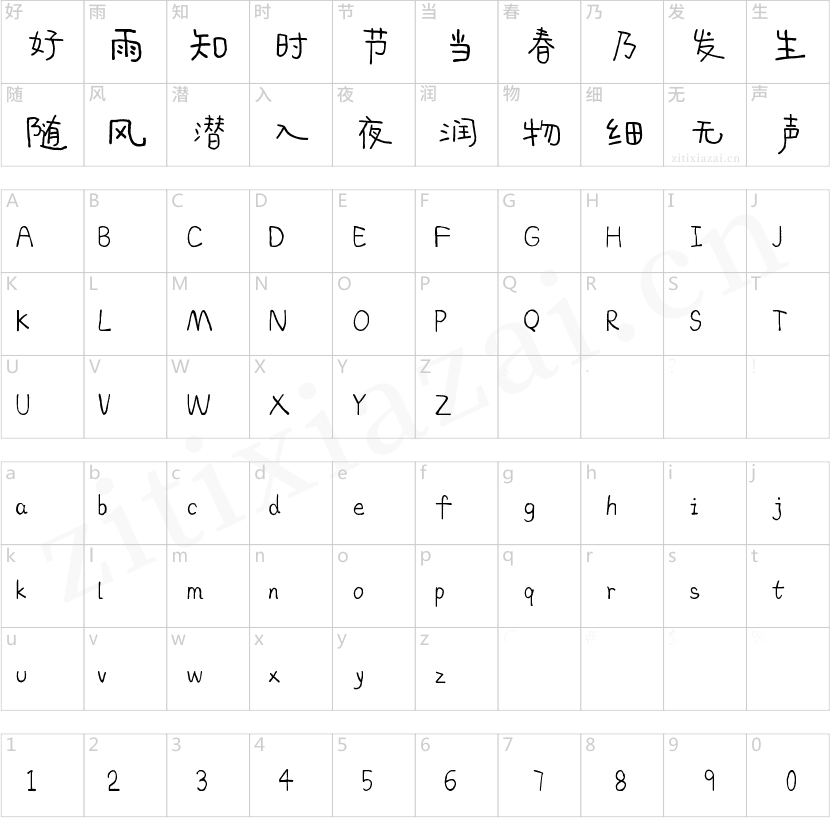
字魂90号-萌趣甜心体
字魂90号-萌趣甜心体,这款字体结构工整、笔画清晰,兼顾美观与易读性,适用于标题、正文、海报、包装、LOGO 等多种场景。字形优雅稳定,风格百搭耐看,适配日常排版与创意设计,让文字呈现更舒适、更具质感。字魂90号-萌趣甜心体一笔一画,皆是细节,以均衡的比例、流畅的线条打造舒适视觉体验,字形端正大气,风格简约现代。无论是商业设计、品牌宣传还是日常排版,都能轻松驾驭,让文字更有格调与力量。字魂90号-萌趣甜心体字体下载。
字魂字体字小魂萌趣甜心体字体是由字魂创意字库设计并生产的一款可商用的字体,被收录于字小魂系列。该字体支持GB-2312标准,包含9170个中文、字母、符号和数字,字体类型偏向硬笔手写,具有活泼、动漫、可爱、简约、时尚、圆润的风格,在市面上广泛用于金融服务、印刷品&包装、母婴等场景。